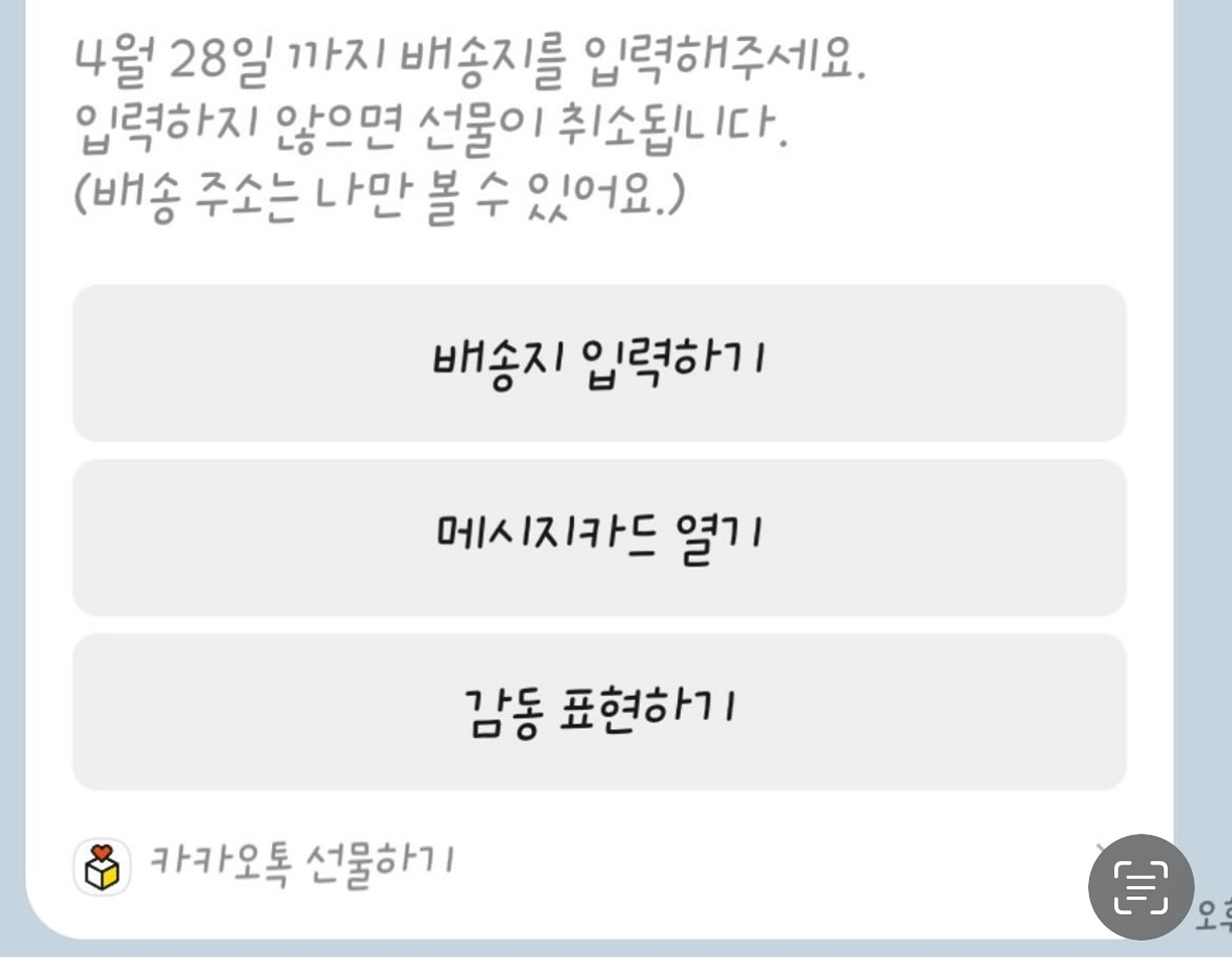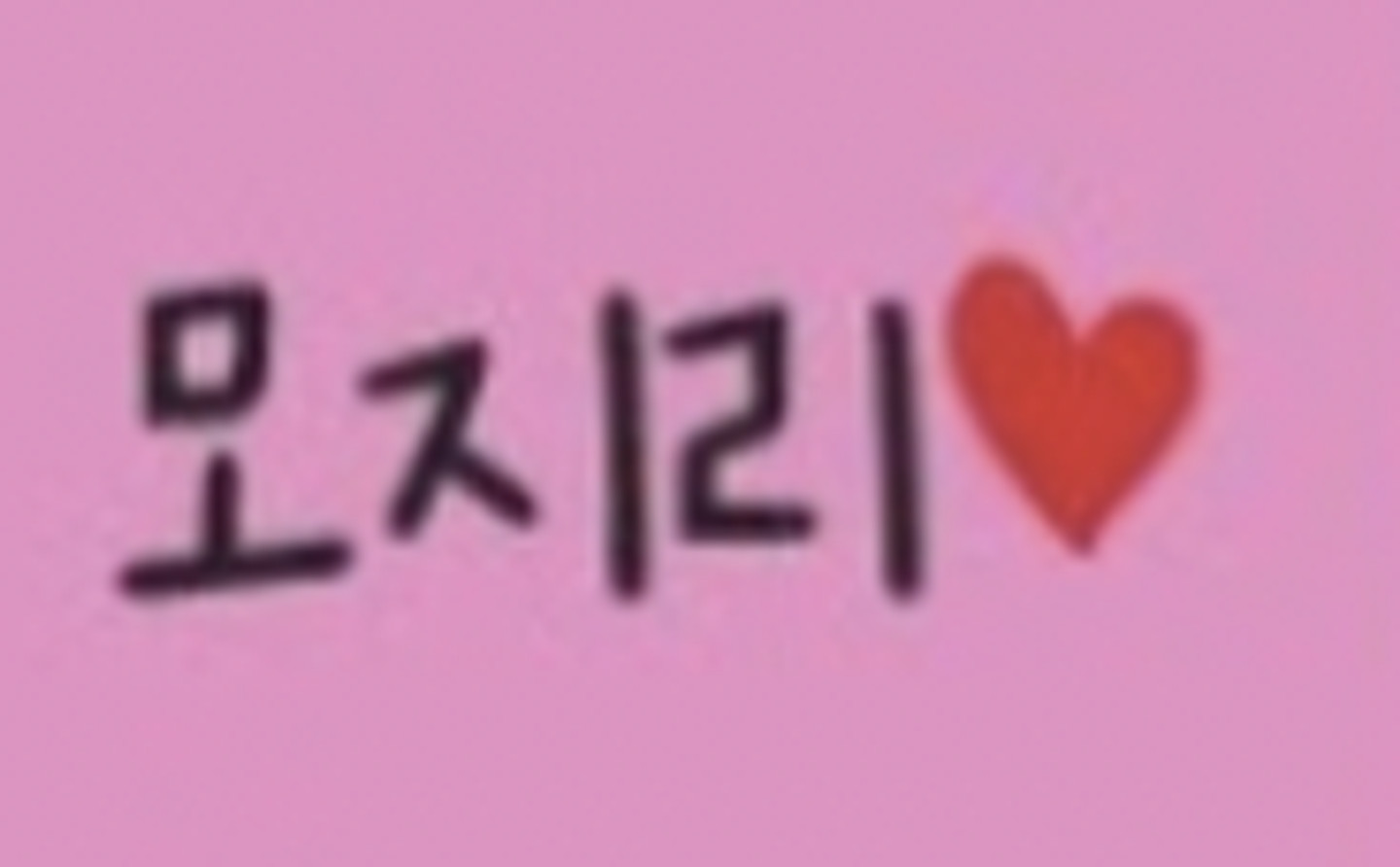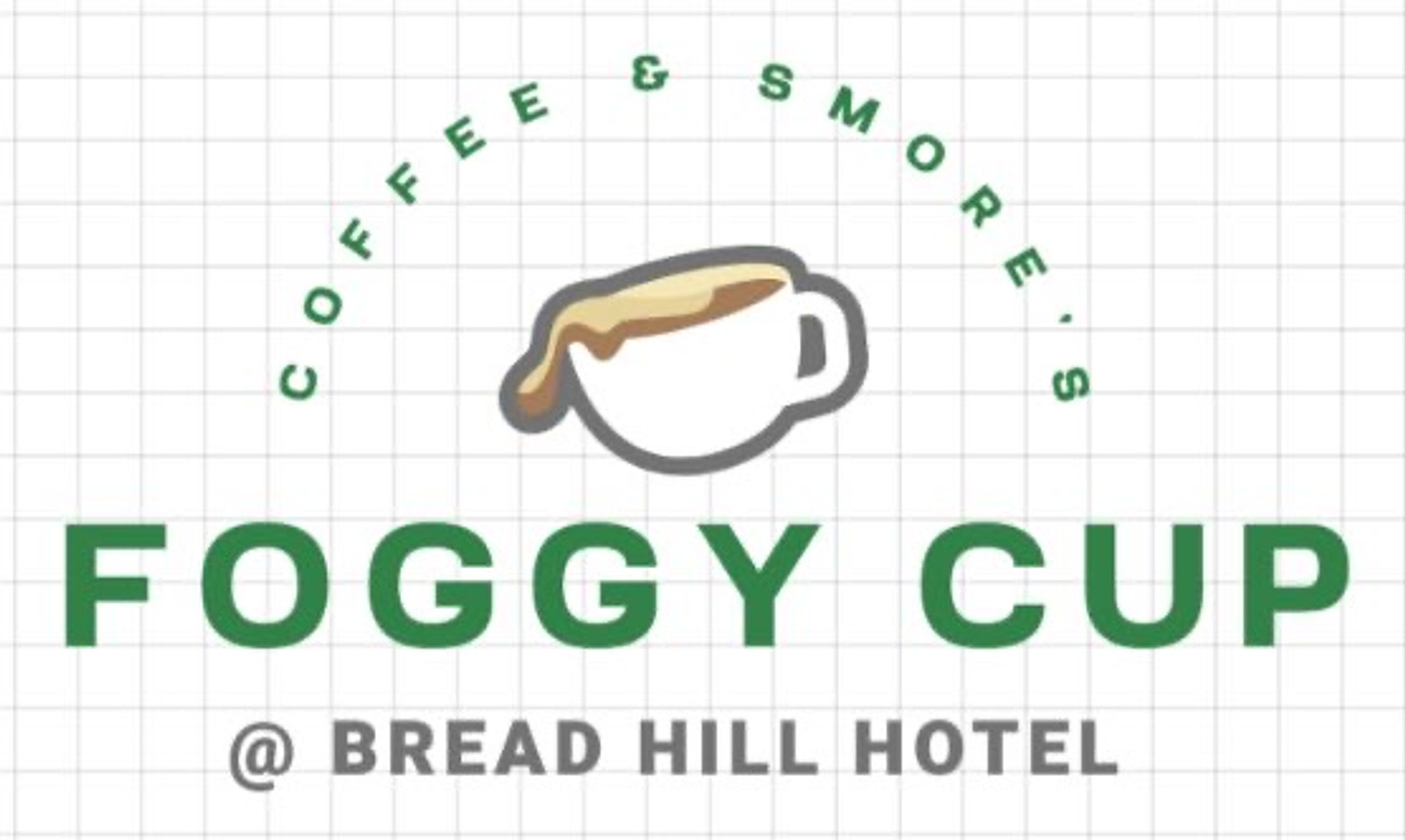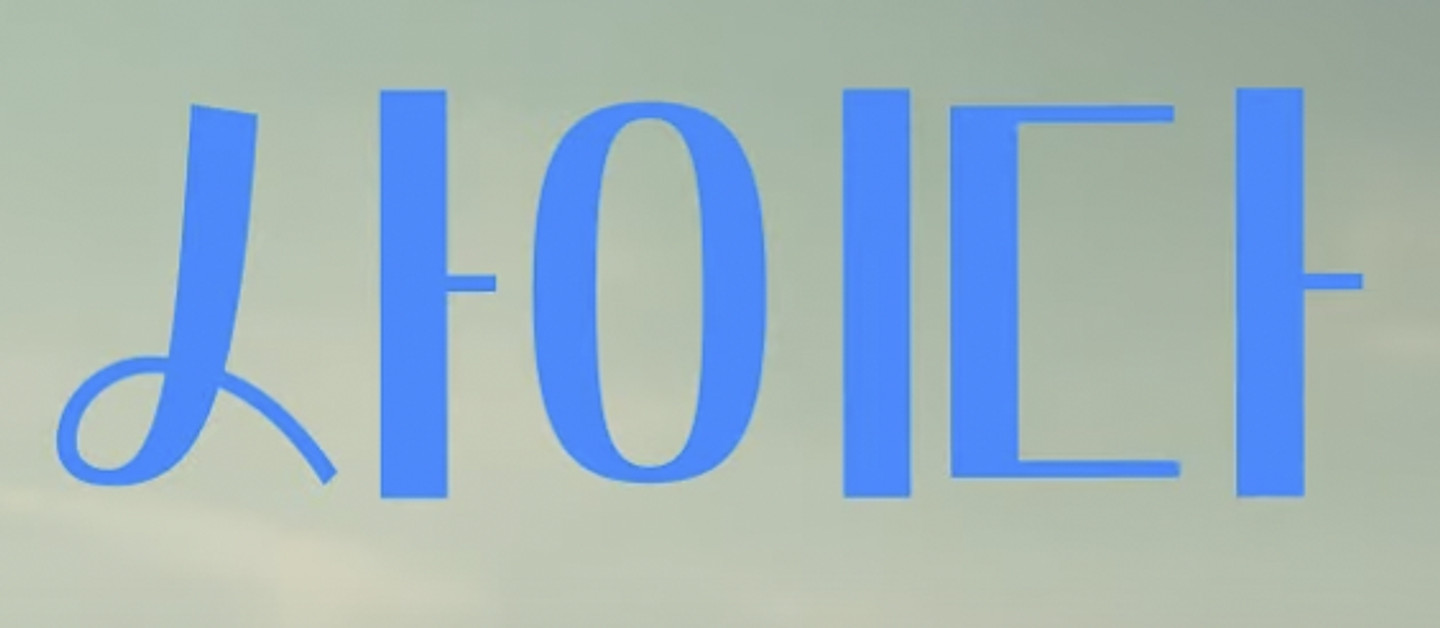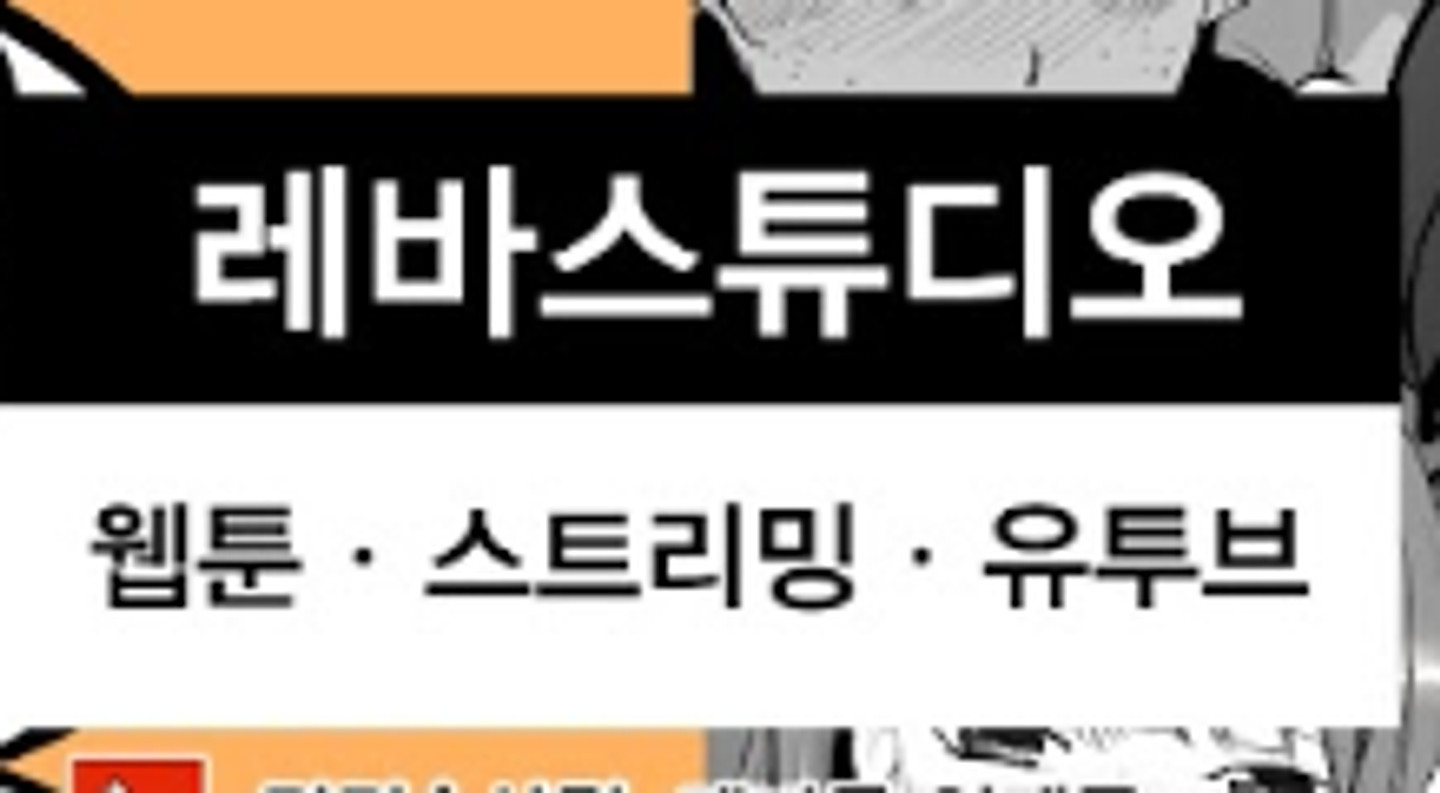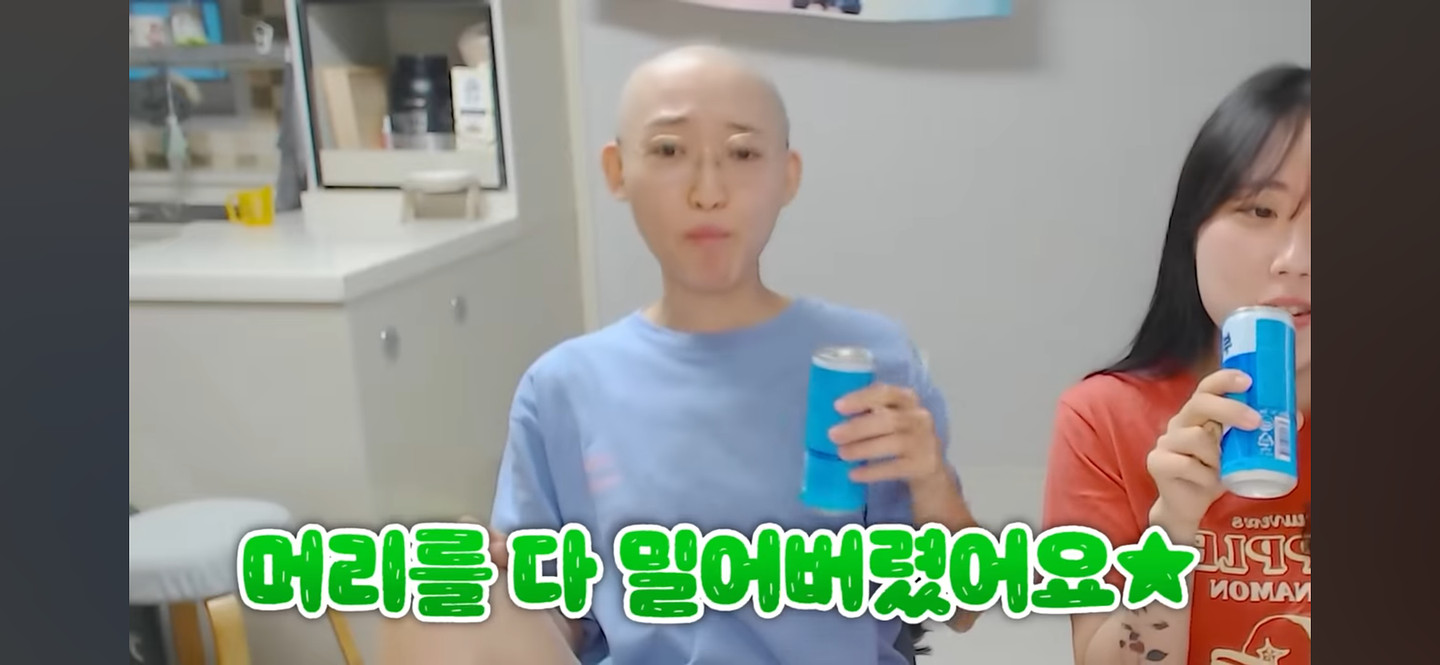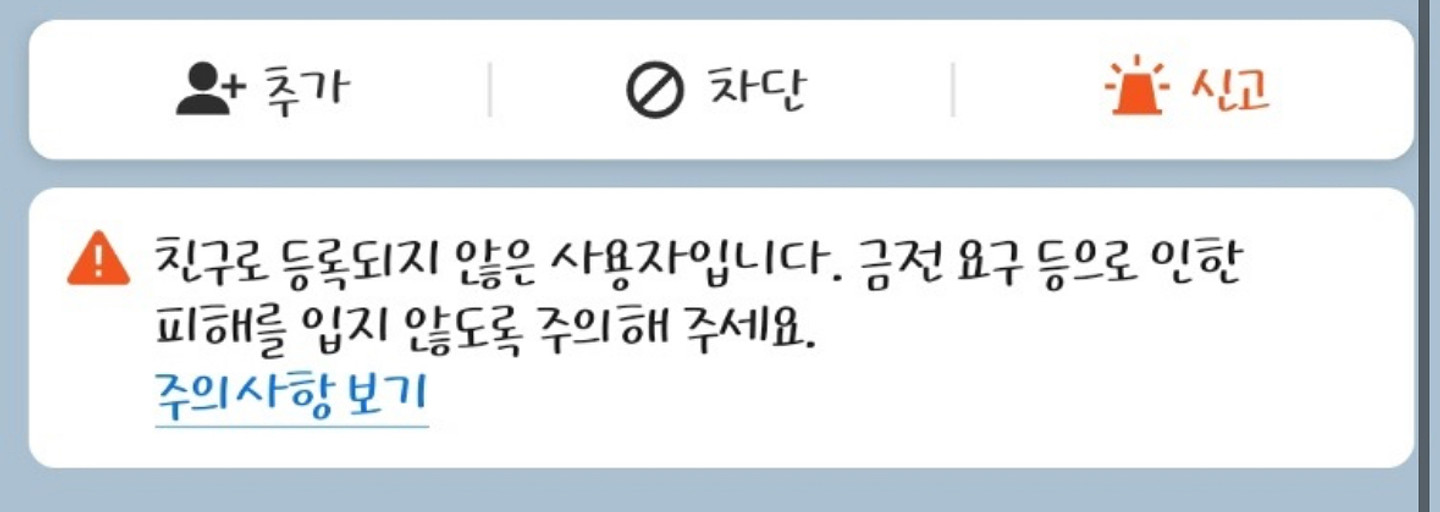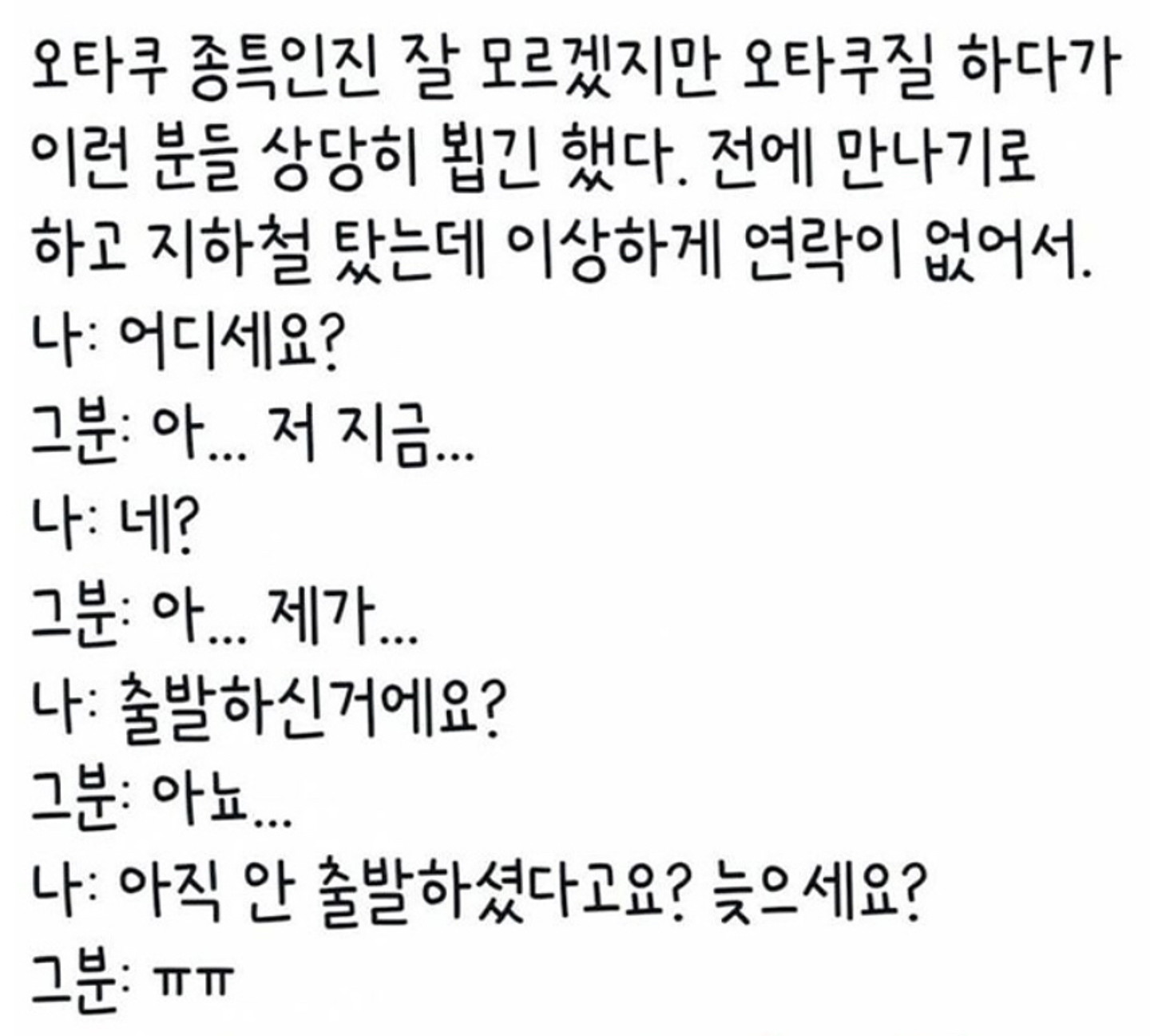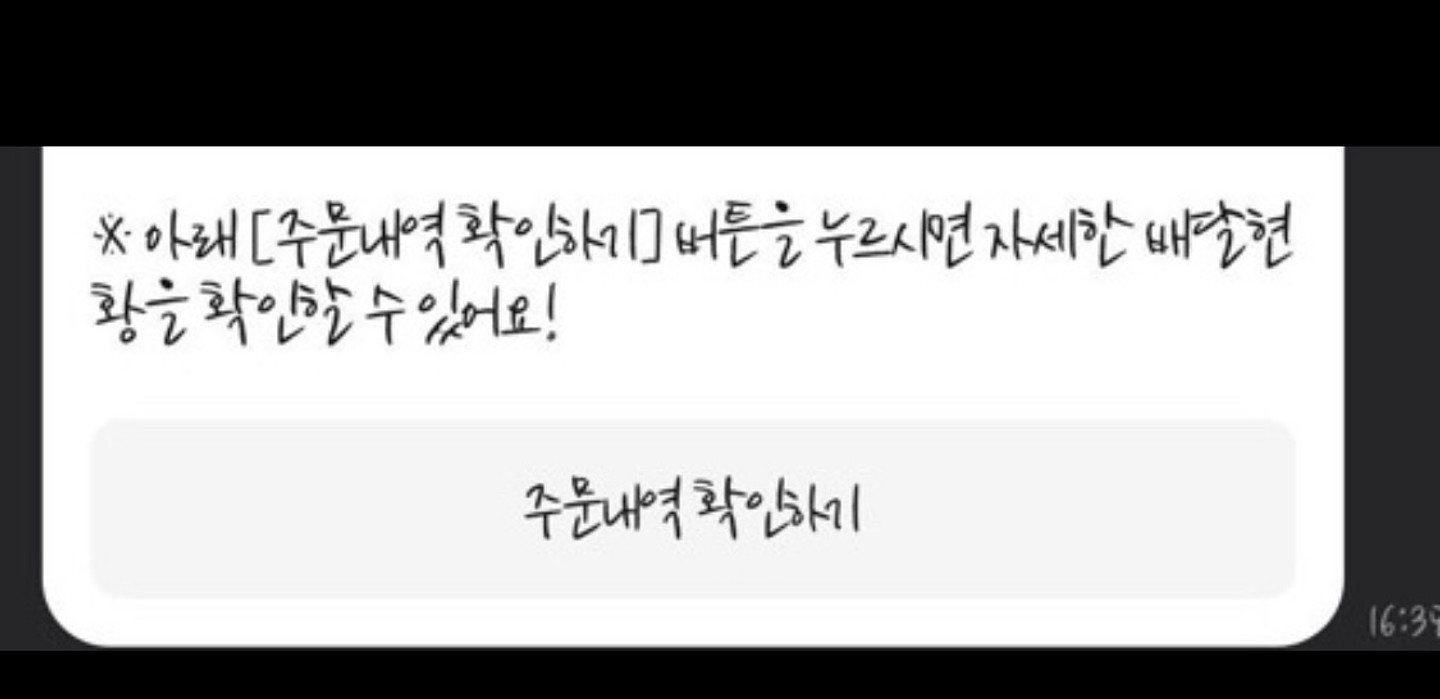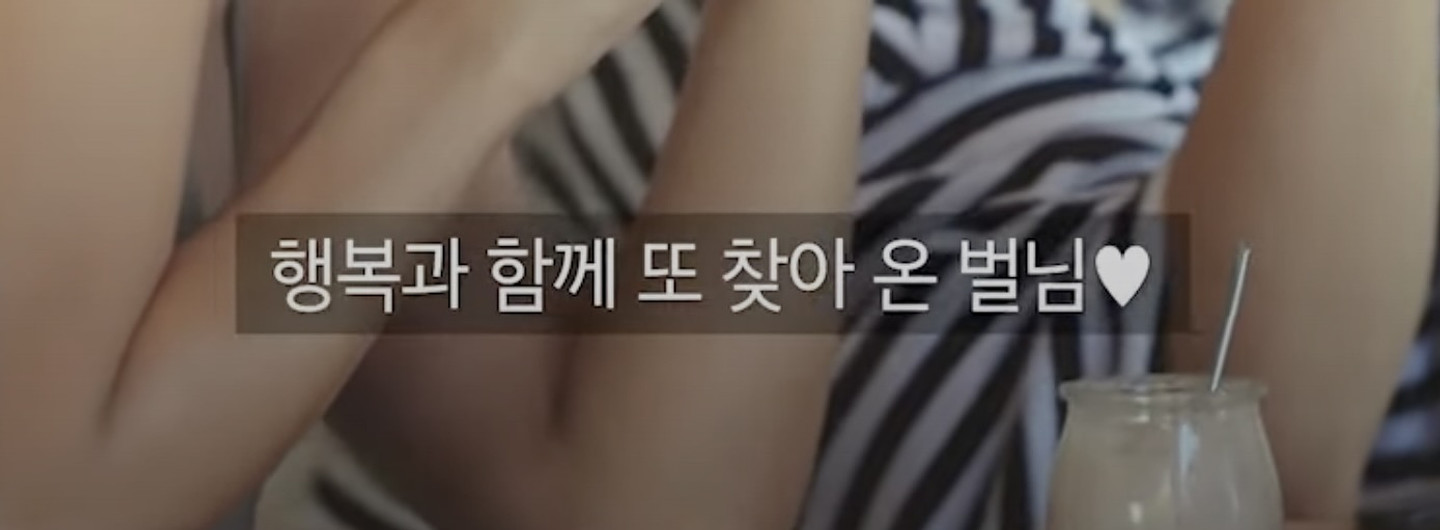
요기 배송안내 무슨 폰트일까요???
CU 편의점에서 본 폰트인데 무슨 폰트인지 아시나요?
영어폰트알랴주세요
이 폰트 뭘까요?ㅠㅠ
모든 것이 마법처럼 괜찮아질 거라고 책에 폰트는 어떤 폰트인가요?
은혼에서 나오는데... 무슨 폰트인가요 ㅠㅠ
한국어랑 일본어 폰트 찾습니다ㅠㅠ
이거 무슨 폰트일까요??
신사장네 어벤져스 무슨 폰트일까요?
멸종위기사랑 뮤비 처음에 나오는 이 폰트 뭘까요ㅜㅜ
이런 폰트나 디자인은 어떻게 만드나요?
에픽에 있는 폰트인데 무슨 폰트인지 급하게 여쭤봅니다ㅠㅠ 선생님들 알려주세요~! ♥
무슨 폰트 인가요~?
이거 무슨 폰트에요ㅜㅜ? 너무 귀여운 폰트라 꼭 찾고 싶은데 아무리 찾아도 안보이드라구여..
무슨 글씨체 인지 궁금합니다 좀 알려 주세요
1이 꺽이고 받침이 잇고 7도 꺽이고 처음에 나눔인가 싶었는데 약간 달라요 아시는분 없을까요?
이미지 검색 돌려도 잘 안나오네요 ㅠㅠ 뭔지 궁금해요
알려주세요~~
이 폰트 아시는분 계신가요? ㅠㅠ
글씨 알려주세용
글씨체 궁금해요~~
글씨체 알고싶어요
인스타에서 본 폰트인데 도대체 무슨폰트인지 모르겟습닞다ㅠㅠ
한글이랑 일본어 둘다 궁금해요..
이 폰트 이름 아시는분 계신가요? 아님 비슷한거라도 아시는분??
서체의 이름을 알고싶어요
jcc 아트센터 로고와 같은 폰트 필요함
유튜브 보다가 폰트가 예뻐서 뭔지 궁금해서 여쭤봅니다 혹시 뭔지 아시는분 계실까요?
이름이 뭔지 너무 알고싶습니다 모른다면 비슷하게 생긴 폰트라도 찾고싶어요...
이 폰트 어떤 걸까요?
눈누 폰트 사이트에서 찾은 서체인데 어떤 서체였는지 기억이 안난다. 찾아줄 수 있나요?
한국백혈병어린이재단 폰트
스포타임 숏츠에서 쓰는 폰트가 너무 궁금합니다 ㅜㅜ 고수님들 한수 알려주세요 ㅜ
이 폰트 이름이 뭔가요
이 폰트 뭔지 알고 싶어요
이 폰트 뭐에요? 너무 알고 싶어요
폰트알려주새여!
무슨 폰트인지 알려주세요! 그리고 저거 그림자효과는 색깔을 완전 검게 만든후에 투명도를 낮춘건가요?
폰트 이름 알려주세요😭😭🥺🥺
번역가 황석희님 전참시에서 사용하신 폰트인데 어떤 폰트인지 궁금합니다. https://www.youtube.com/watch?v=KZPW1dqSKg4
"평촌교회" 폰트가 궁금합니다
전소미 브이로그 글씨체 궁금합니다!
이거 어떤 폰트인가요??
궁금해요!!
성수동 가서 우연히 봤습니다 무슨 폰트일까요??
무슨 폰트인지 아시는 분 계신가요?
어떤 폰트인지 너무 궁금해요
이런 웹 사이트 (예를들어 네이버 검색 할 때 나오는) 폰트는 무엇인가요? 디자인을 할 때, 이런 포털 느낌 내기 위해선 어떤 폰트를 사용해야 자연스러운가요?
이 고딕체 가 너무 궁금합니다!!
영문 폰트 뭘까여
여기 1박2일 시즌3때 사용된 이름표 자막이라고 하는데 여기에 들어간 글자의 폰트가 뭔지 알려주실 수 있나요?
영문 폰트 뭔지 알 수 있을까요?
폰트 알려주세요!
예전 00년대에 많이 쓰던 폰트인데 뭔지 아시는 분 계실까요?